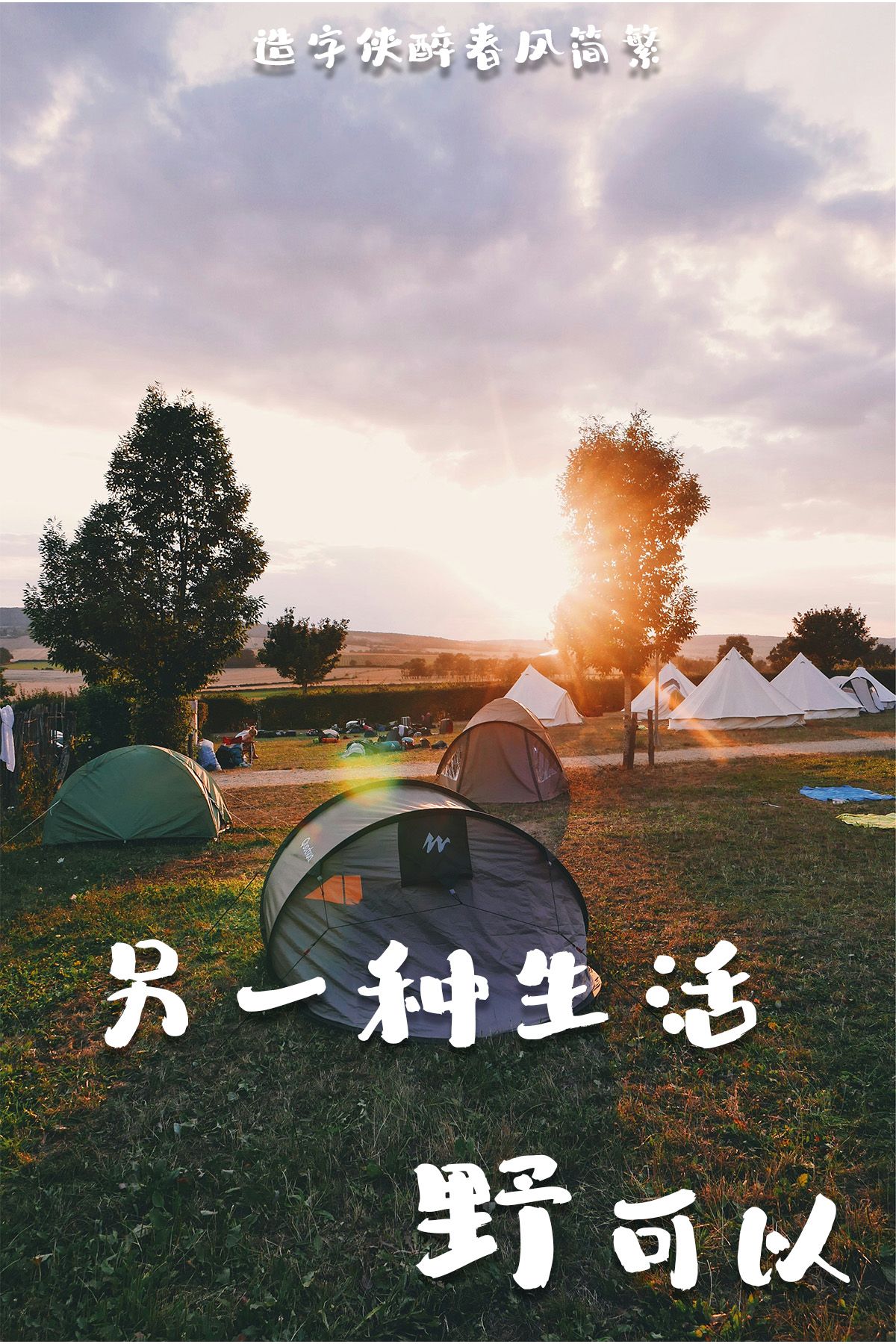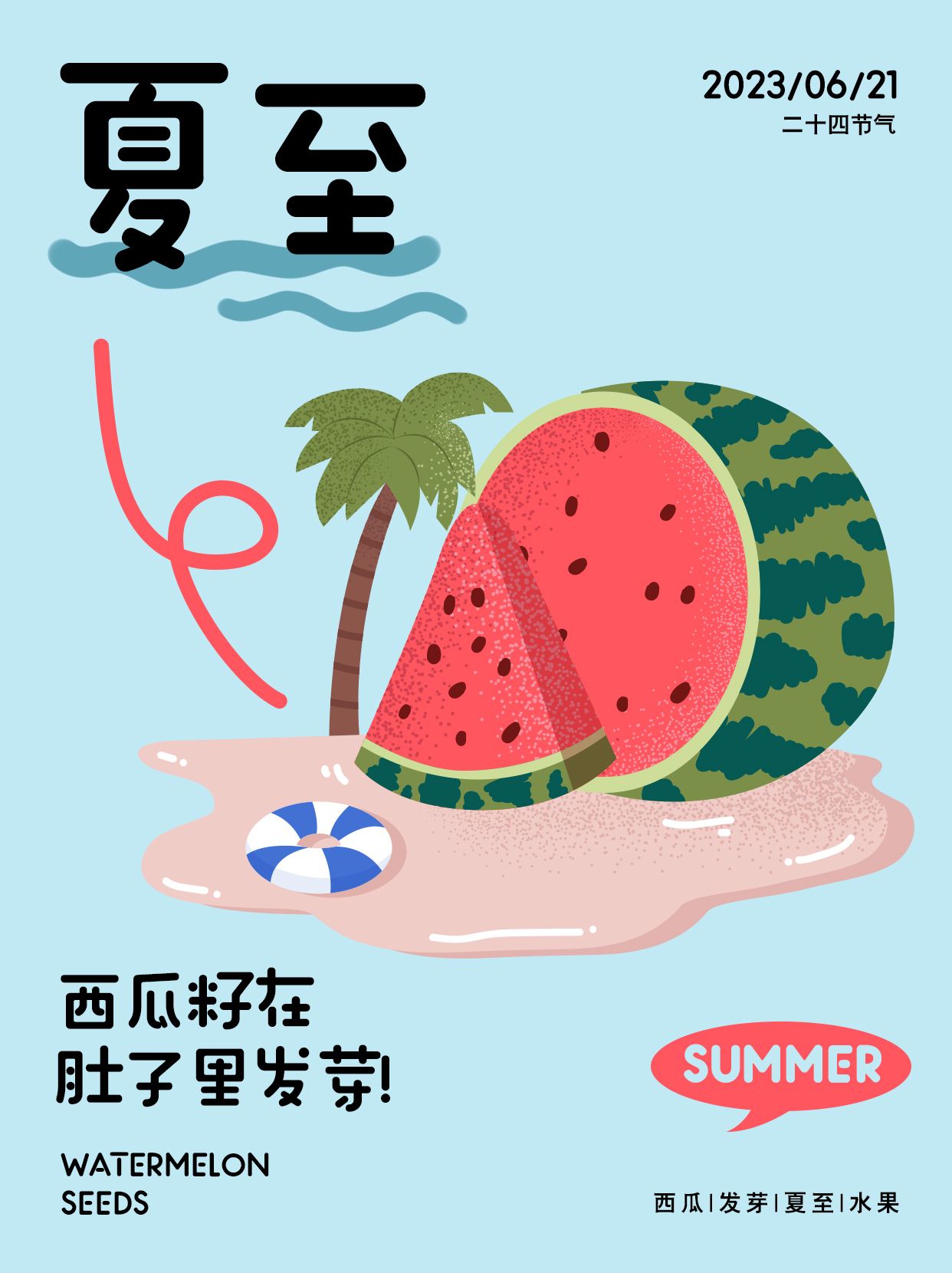
热门综艺《种地吧2》,用什么字体呈现视觉盛宴?
综艺节目作为现代娱乐的重要组成部分,其视觉呈现对于吸引观众、传递节目氛围至关重要。字体作为视觉元素之一,在综艺节目中扮演着举足轻重的角色。下面,就为大家推荐几款适合综艺节目的字体,以助您打造绚丽视觉盛宴。
一、活力四溢:励字小桃气简繁 大圆
励字小桃气简繁 大圆以其活泼、动感的特质,成为综艺节目的首选。其流畅的线条和多变的设计风格,励字小桃气简繁 大圆能够很好地契合综艺节目轻松、愉悦的氛围。无论是用于节目标题、字幕,还是特效文字,励字小桃气简繁 大圆都能为节目注入无限的活力,吸引观众的眼球。
二、时尚先锋:励字志向黑简 超粗
对于追求时尚感和现代感的综艺节目来说,励字志向黑简 超粗无疑是一个不错的选择。励字志向黑简 超粗设计简洁、线条清晰,又不失时尚韵味。它能够凸显节目的现代气息,同时传递出一种高品质的视觉感受。在关键信息提示、嘉宾介绍等环节使用励字志向黑简 超粗,定能让观众眼前一亮。
三、个性张扬:造字侠醉春风简繁 苍劲
手写体以其亲切、自然的风格,深受观众喜爱。在轻松、幽默的综艺节目中使用造字侠醉春风简繁 苍劲,能够拉近与观众的距离,营造温馨的节目氛围。造字侠醉春风简繁 苍劲适合用于表达节目中的个性和情感元素。
四、主题契合:励字暴风简 超级黑
针对不同类型的综艺节目,我们还可以选择与之主题相契合的特色字体。例如,在音乐类节目中,可以选用音符形状的字体,增强音乐氛围;在文化类节目中,则可选用古风字体,凸显综艺风格。励字暴风简 超级黑能够让节目更具辨识度和吸引力。
综艺节目字体的选择丰富多样,关键在于根据节目的主题、风格和氛围进行精心挑选和搭配。通过合适的字体设计,我们可以为观众呈现一场精彩绝伦的视觉盛宴,让他们在观看节目的同时,享受到字体艺术带来的美妙体验。